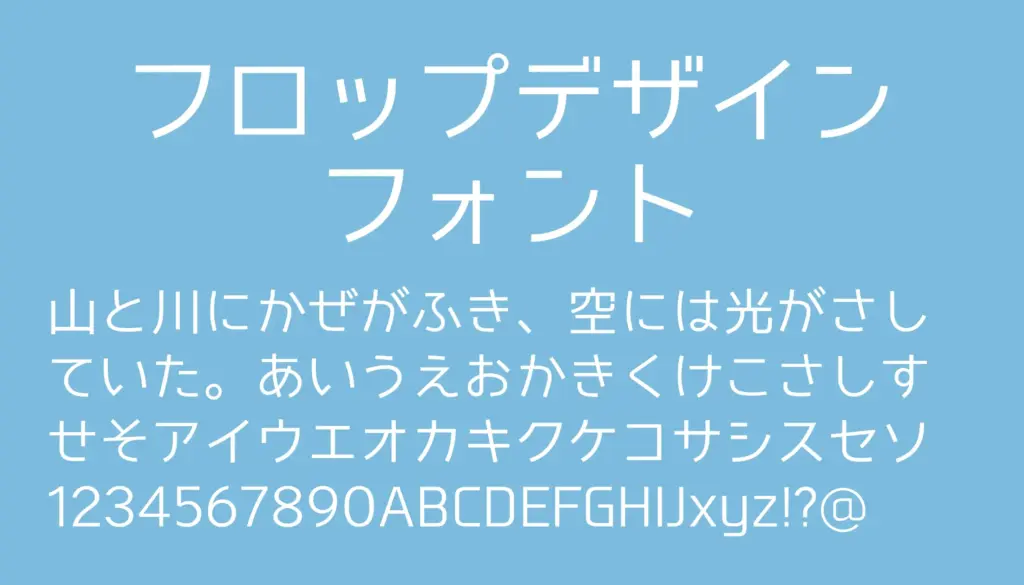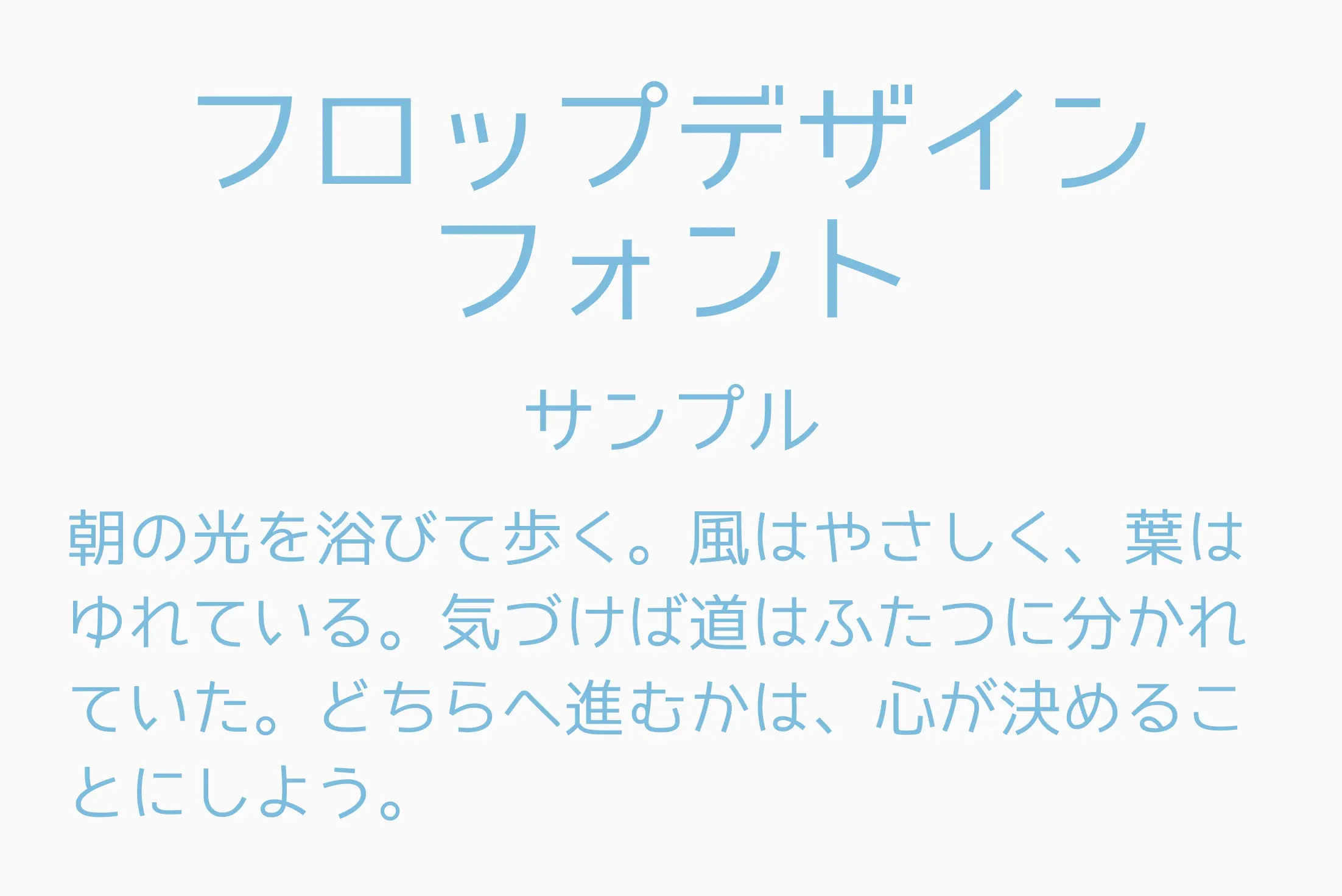
スタンダードなゴシック体をベースに、現代的な抜け感と安定した視認性を追求したデザインフォントです。シンプルでありながらも程よい個性を感じさせる仕上がり。ポスターやバナー、Webデザインはもちろん、ビジネス資料でも活用できる万能型。ミニマルでクールな印象を与えたい場面に最適な一本です。
フロップデザインフォント